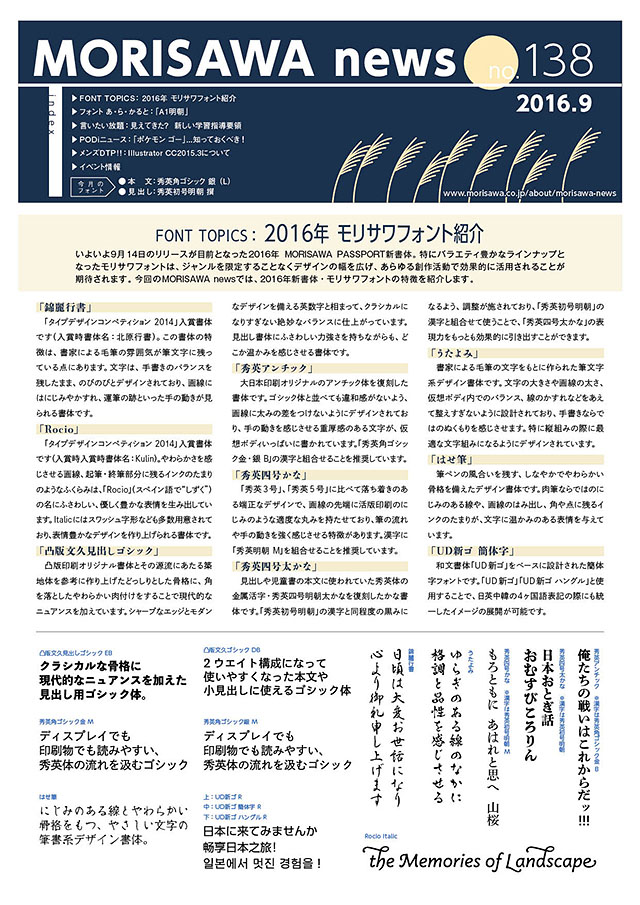
モリサワニュース
2016年9月号第138号
FONT TOPICS:2016年 モリサワフォント紹介
9月14日に提供が開始される2016年 MORISAWA PASSPORT新書体に関して、それぞれの書体の特長や字形を示しながらご紹介します。
「タイプデザインコンペティション 2014」入賞の「錦麗行書」や「Rocio」をはじめ、「うたよみ」や「はせ筆」など筆書系フォント、伝統的な書体などバラエティ豊かなラインナップとなっています。
フォント あ・ら・かると:「A1明朝」
1960年に発売されたオールドスタイルの明朝体「A1明朝」は、時代を越えて愛され続けています。このたび「活字ブックマーカーTM」として、装いも新たに皆さまのお手元にお届けします。